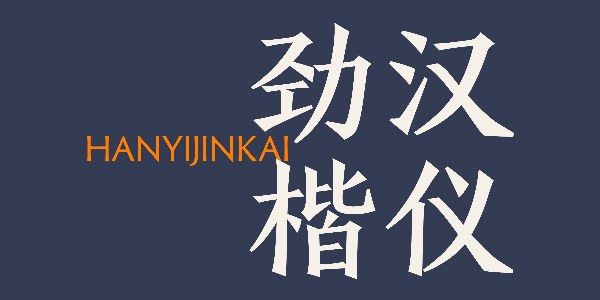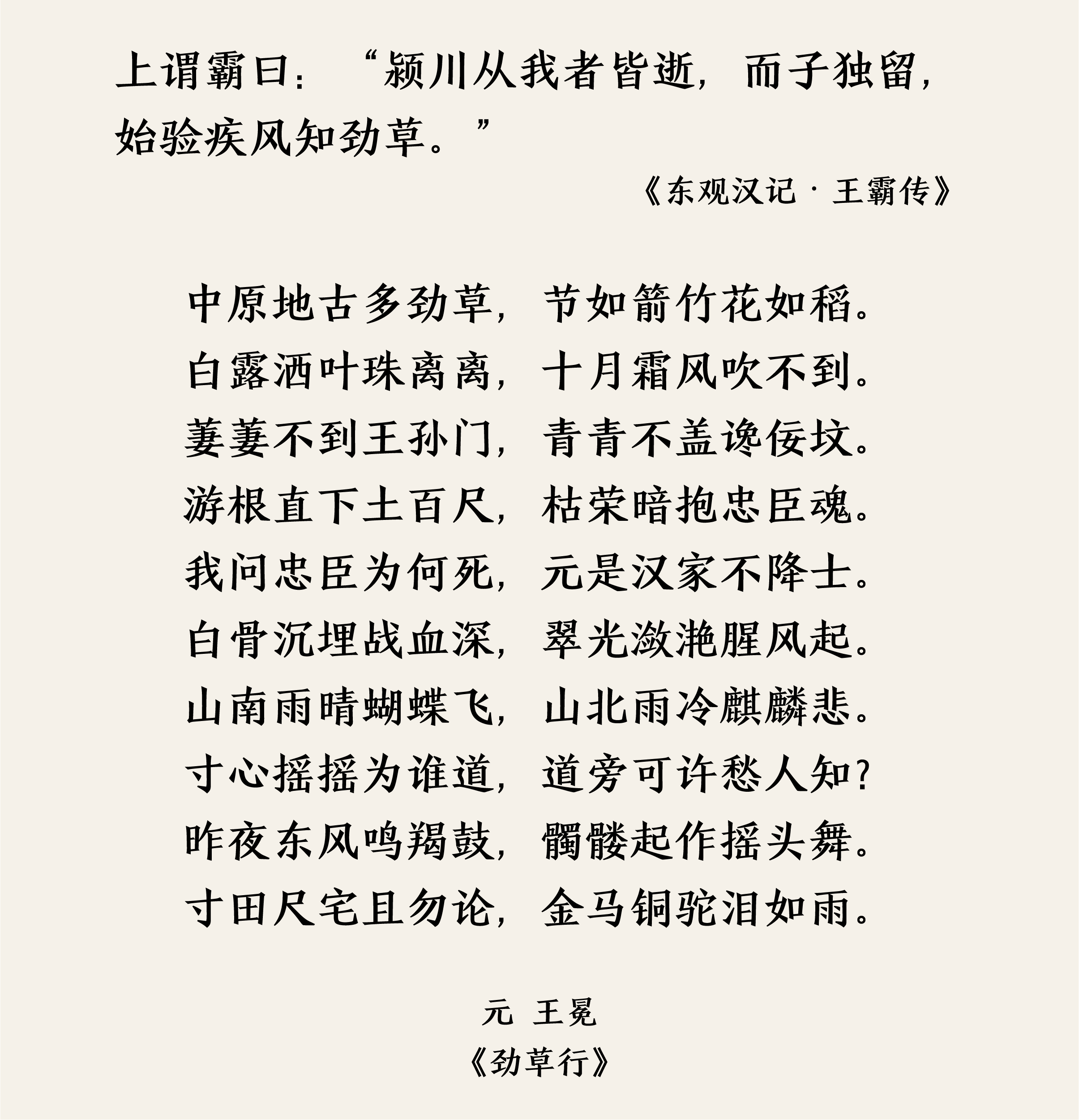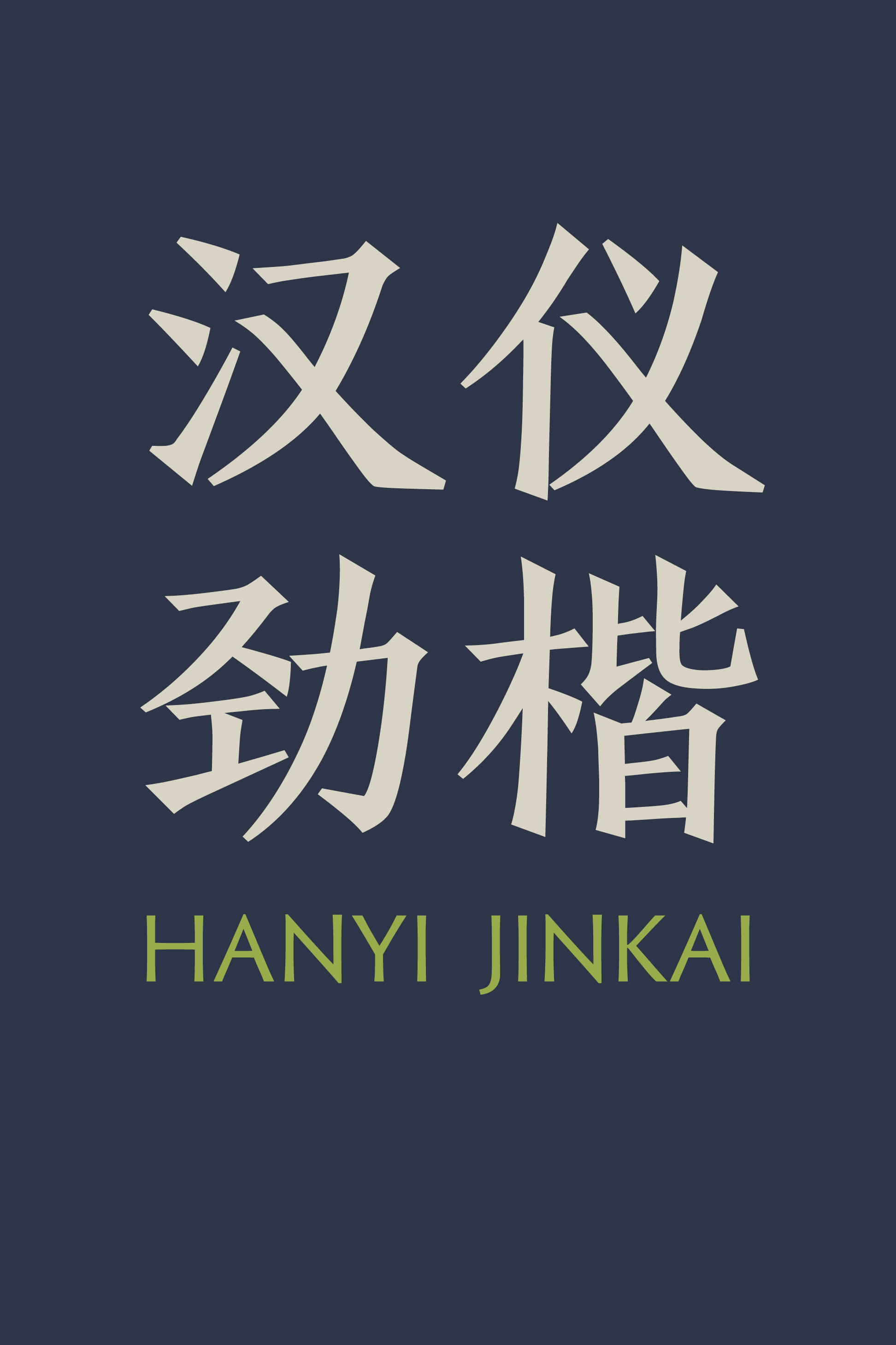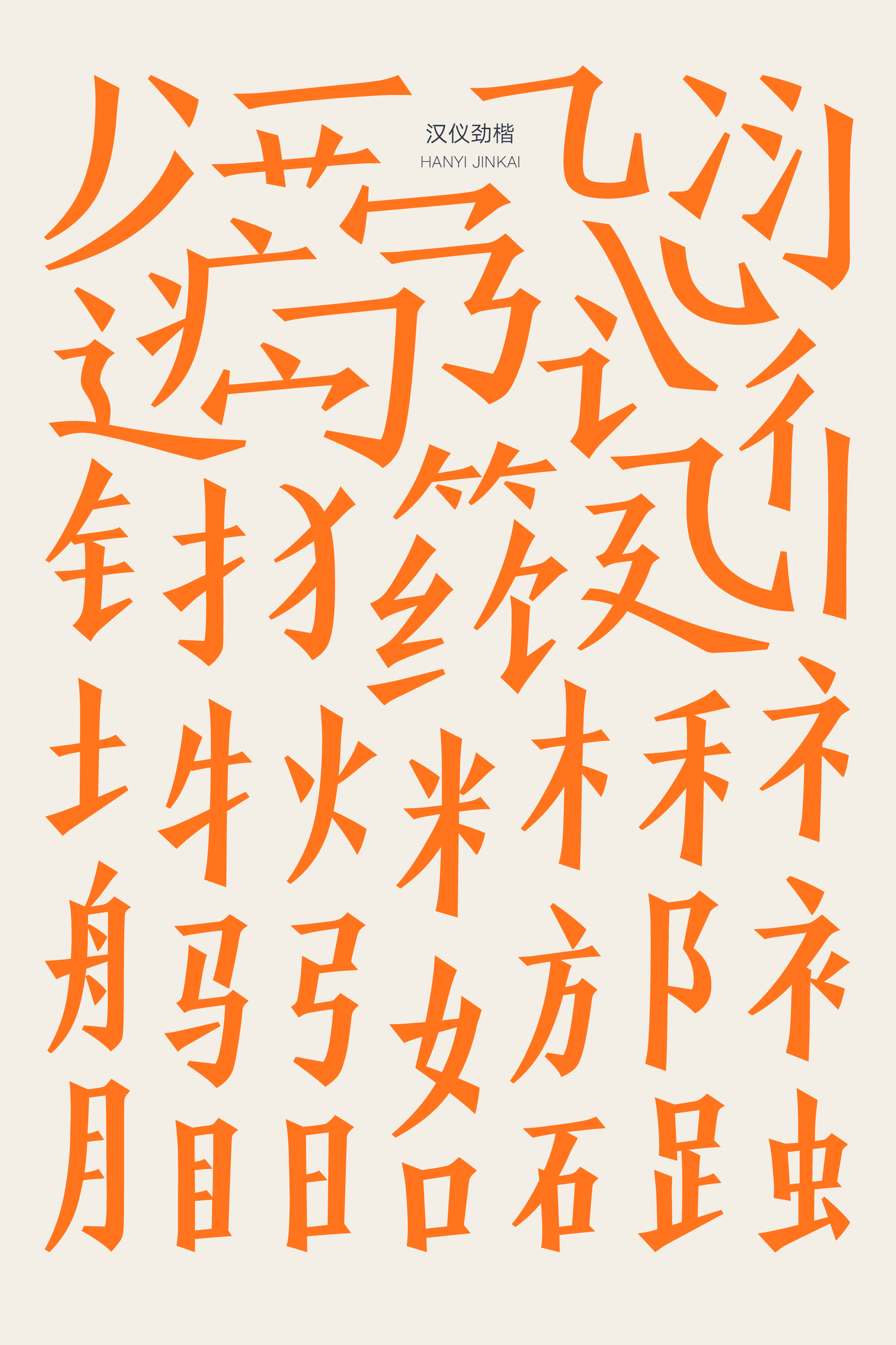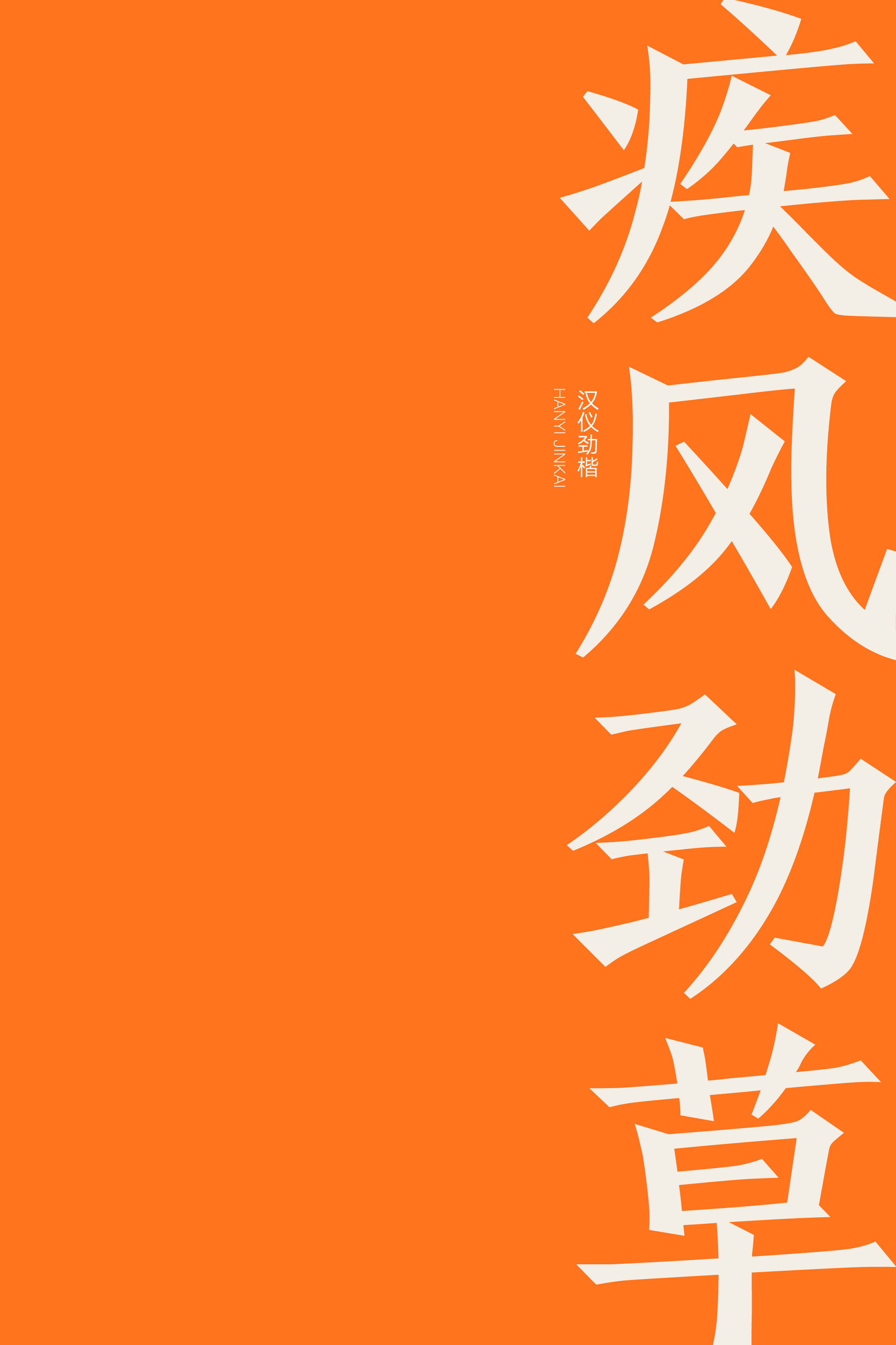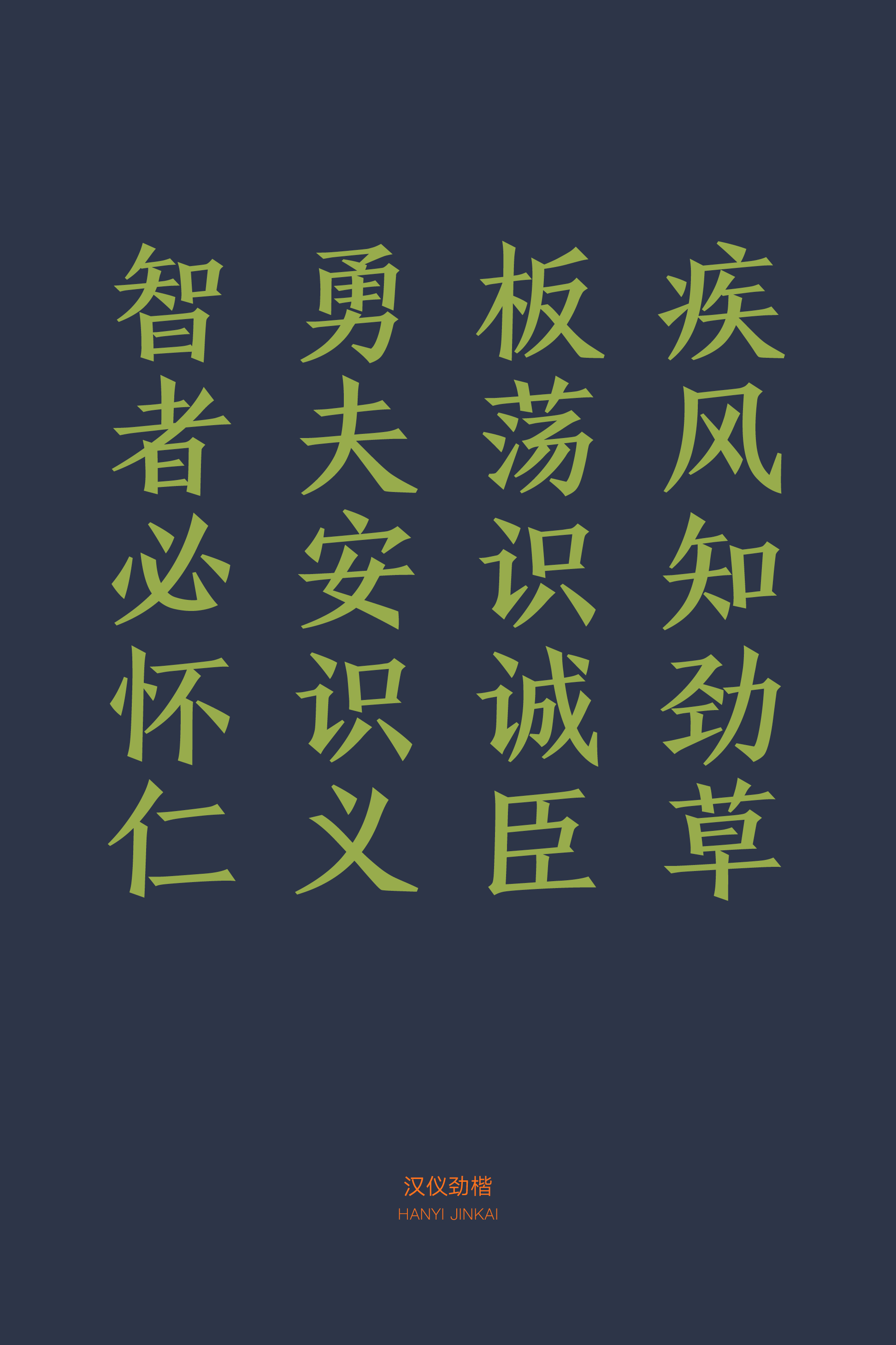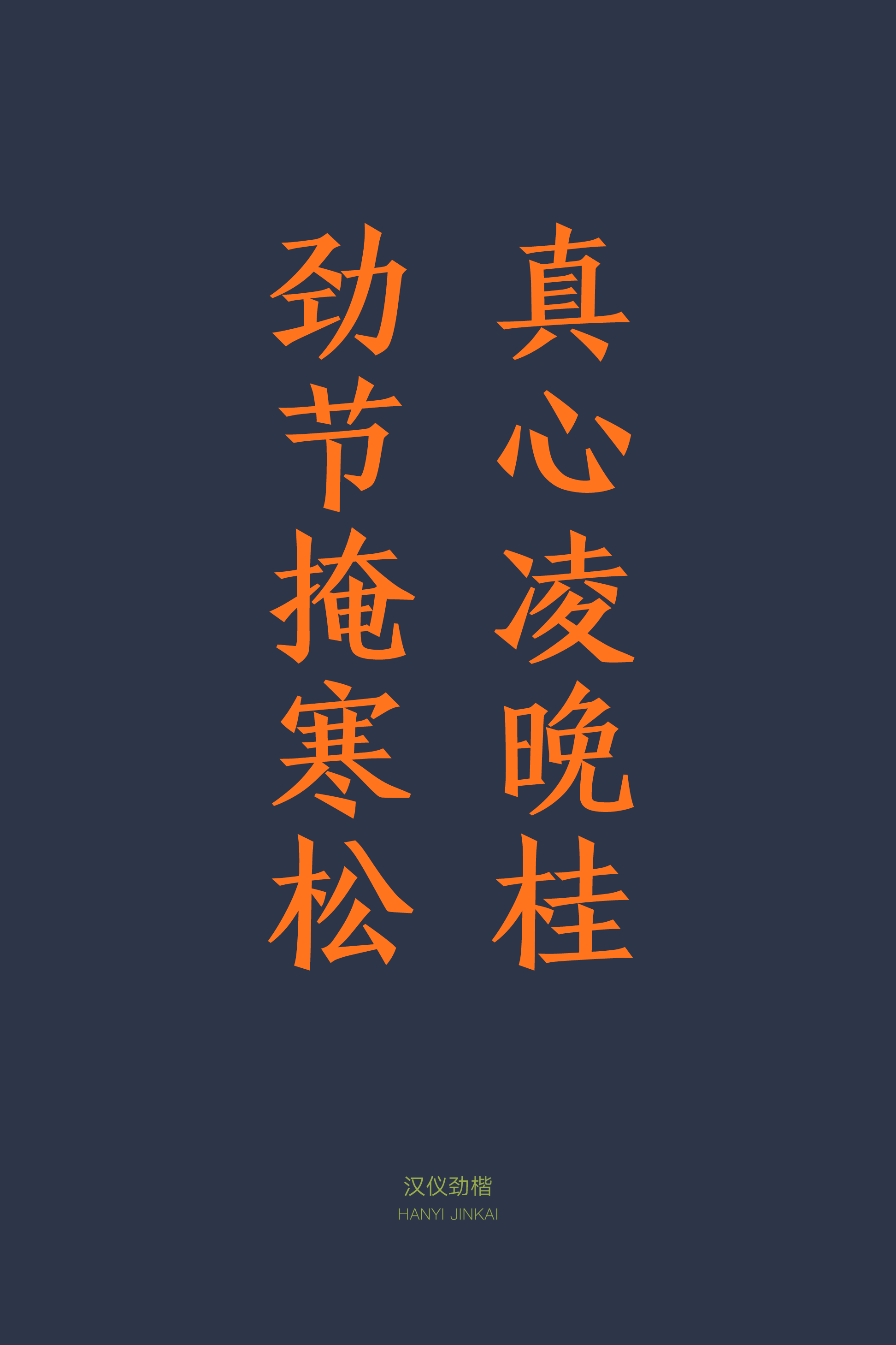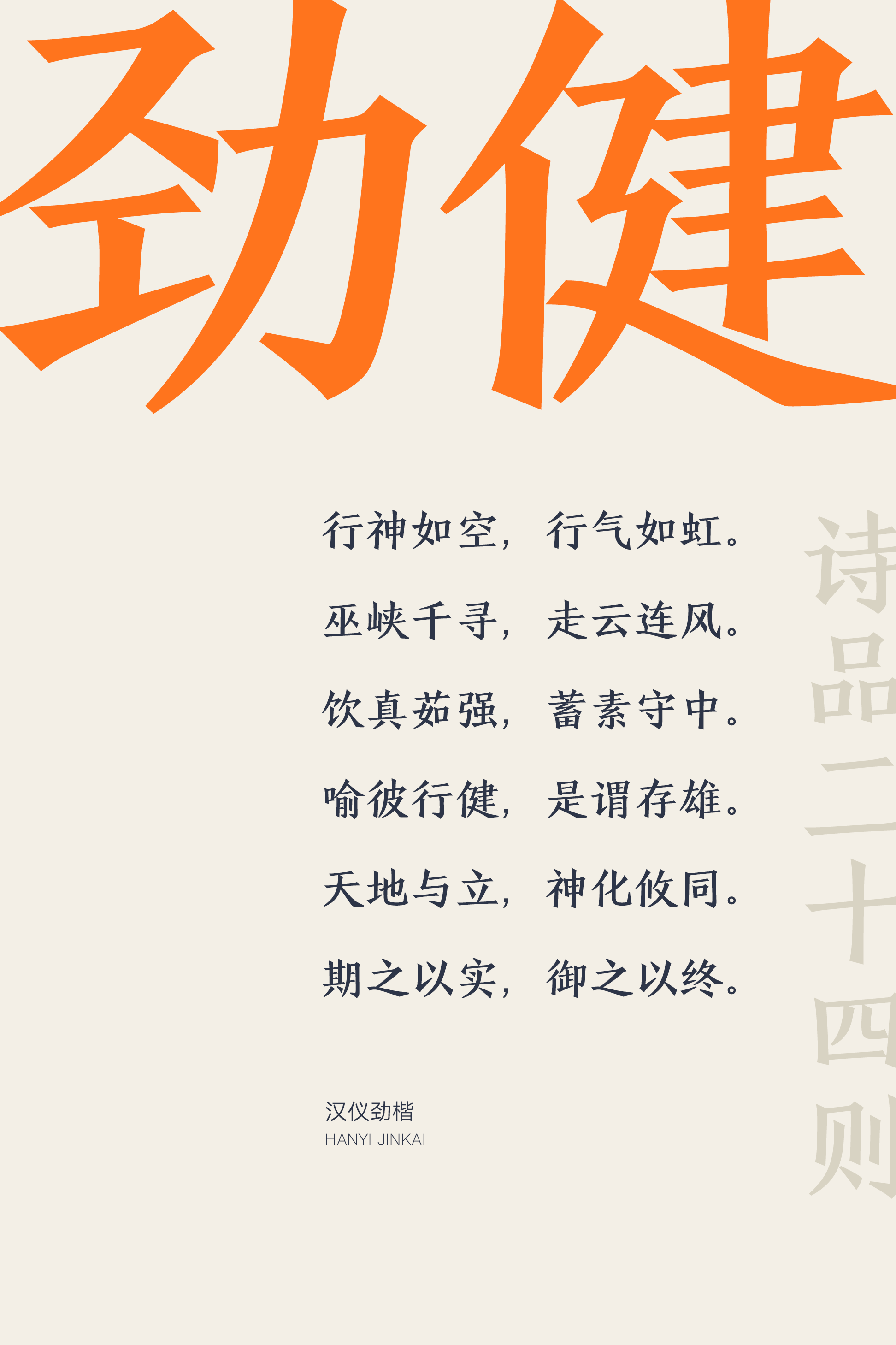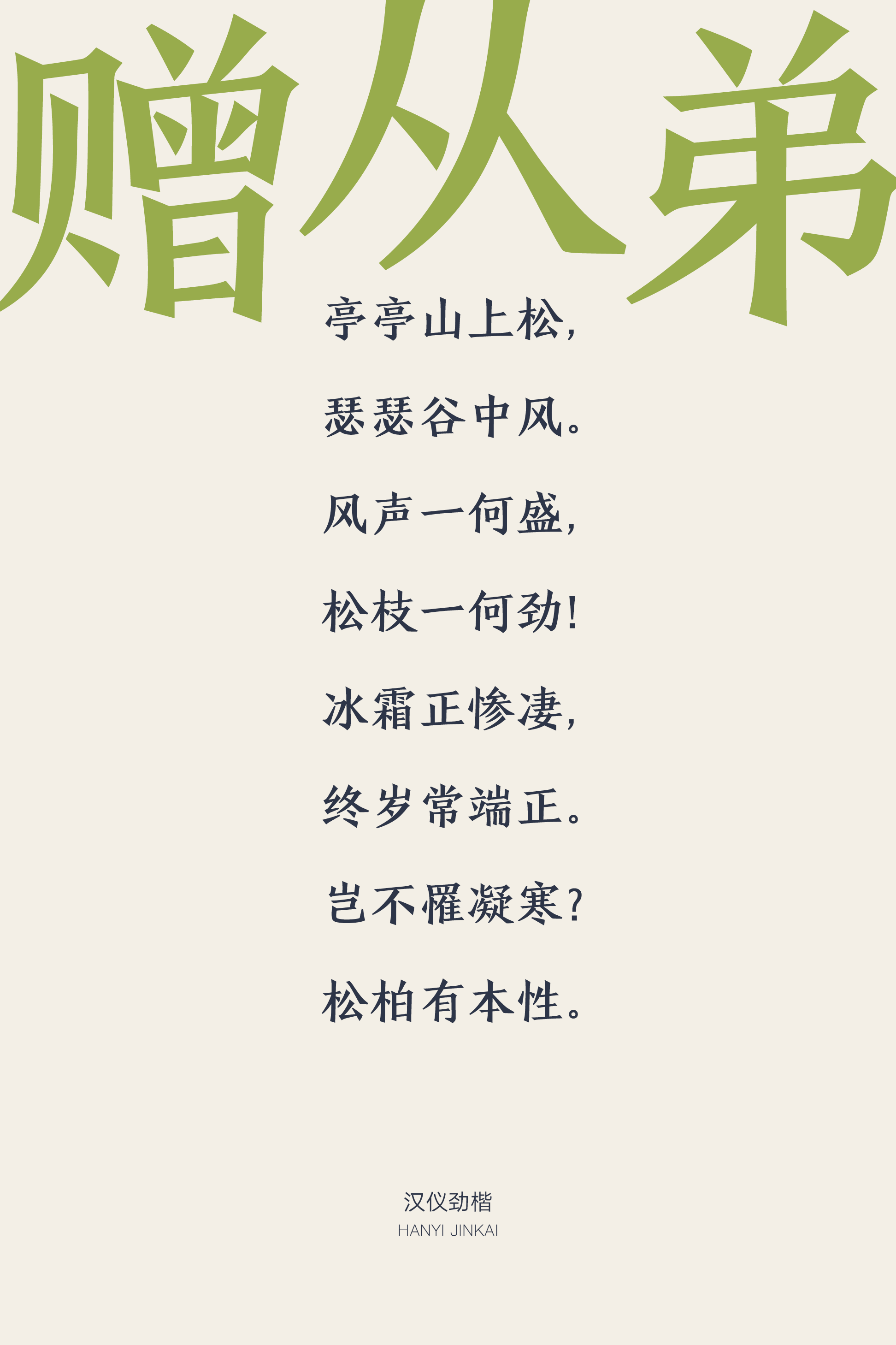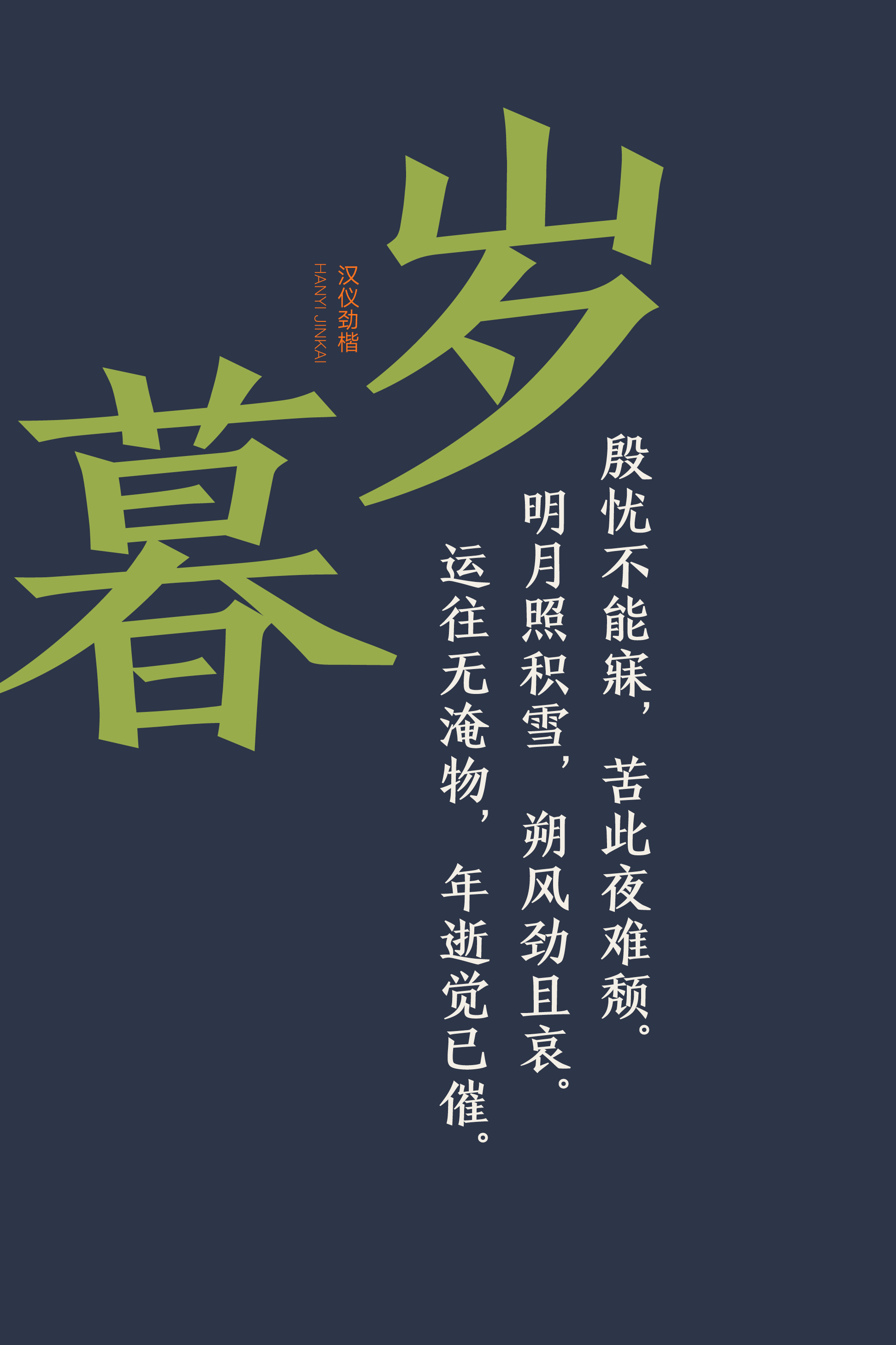
汉仪劲楷
汉仪劲楷,端正而劲健,将楷体与现代风格相结合,并融入《常岳等百余人造像记》的特点。汉仪劲楷由汉仪字库签约作者宋莹创作,字形工整大方,以方峻之笔构成,笔画简略有力,提按转折交代清晰,横细竖粗,兼具古趣与现代性。这款字体适用于标题及正文排版,端正秀丽,与正式、传统、文雅的使用场景十分相称。
《常岳等百余人造像记》为北魏造像记书法,形制上采用方界格,态度恭谨,书风已可见唐楷法度森严之气息,书刻俱精,纤毫毕现。
汉仪劲楷融合此造像记的写刻特征,结字方整,端正秀丽。
方峻笔画简略有力,提按转折交代清晰,横细竖粗。
排版工整大方,用作正文排版带来舒适的阅读体验。